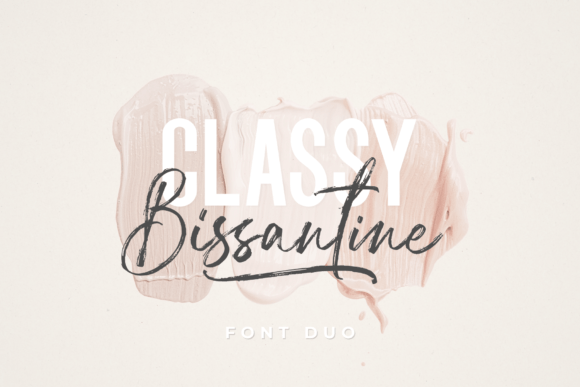
Classy Bissantine Duo
Trouver les bons éléments de conception peut être un défi, mais Classy Bissantine Duo propose une collection exceptionnelle qui rehausse instantanément votre travail.
Que vous créiez des produits POD (impression à la demande), des invitations de mariage ou des visuels pour les réseaux sociaux, Classy Bissantine Duo est un choix idéal.